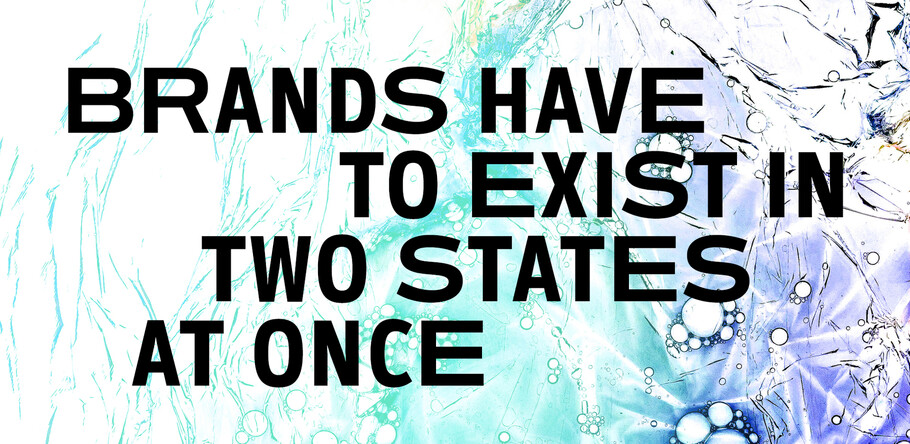
Wie Ihre Marke auch auf kurvenreichen Kundenreisen die Spur hält.
„ Manchmal braucht eine Marke nichts anderes als Schrift. Die muss dann aber auch richtig gut funktionieren. “
Moderne Marken sind schon lange keine statischen Gebilde mehr. Sie werden heute agil und anpassungsfähig geführt, ständig bereit, auf Veränderungen der Kundenerwartungen zu reagieren sowie neue Technologien und Herausforderungen aus anderen Märkten und Sprachen anzunehmen.
In gewisser Weise müssen Marken zwei Aggregatzustände gleichzeitig annehmen – fest und formbar, so dass sie ihr Kontur jederzeit dehnen können, ohne das innere Gerüst zu gefährden. In der Natur leistet Vergleichbares nur Wasser, das fließen, gefrieren und verdunsten kann, in den Bergen seinen Weg findet und riesige Ozeane füllt, dem Wesen nach aber immer es selbst bleibt.
Das Ziele eines jeden Markenmanagements ist die flexible Marke, die es Mitarbeitern und Teams erlaubt, mit ihr zu experimentieren und sie anzupassen, wobei ein solides Inneres dafür sorgt, dass sie nicht auseinander fällt.
Die unheimlich expandierende Marke.
Laut Adobe geben 71 Prozent der Unternehmen an, heute zehnmal so viele Bausteine zu erstellen wie zu Beginn des mobiles Zeitalters. Diese bemerkenswerte Zahl verdeutlicht den vielleicht wichtigsten Aspekt beim Branding von heute: Der Weg zum Kunden führt in mehr als nur eine Richtung.
„ 71 Prozent der Marken erstellen heute zehnmal so viele grafische Bausteine wie zu Beginn des mobilen Zeitalters. “
Stattdessen erweist sich die Customer Journey heute als ein zunehmend fragmentiertes Netz aus divergierenden Strömen. Die Reise eines jeden Kunden weist einzigartige und manchmal subtile Unterschiede auf, selbst wenn sie alle an ähnlichen Orten beginnt oder endet, zum Beispiel auf einem Mobilgerät. Es gibt Tausende unterschiedlicher Modelle, die weltweit in Benutzung sind, mit einem breiten Spektrum an technischen Möglichkeiten und einem noch breiteren Spektrum von Benutzerinnen und Benutzern. Kein einzige Kundenerfahrung ist mit einer anderen identisch.
„Die Kunden sind an mehr Orten als je zuvor, rein geografisch aber auch hinsichtlich der Hardware und des Betriebssystems, das sie benutzen“, sagt James Fooks-Bale, Creative Director bei Monotype. „Und wenn man glaubt, sich optimal eingerichtet zu haben, kommen schon wieder Nachfolgemodelle, eine neue Plattform oder eine neue Art der Content dazu“, ergänzt er.
Wir sind sicherlich noch nicht am Ende dieser Entwicklung angekommen. Schon in naher Zukunft können Marken mit neuen Innovation, Expansionen und mit einer Verlagerung der Kundenerwartungen rechnen, was die Menge und die Vielfalt der Berührungspunkte, die eine Marke zu managen hat, weiter diversifizieren wird. Auch wenn viele auf eine Verlangsamung dieser Dynamik hoffen: neue Technologien in den Bereichen Automatisierung, Personalisierung, Virtual Reality, mehr Plattformen und verbesserte Hardware deuten eher drauf hin, dass die industrielle Welt sich weiter verzweigt.
Schriften sind eine unverwüstliche Klammer.
Auch die flexibelste Marke braucht immer etwas, das sie zusammenhält, was die Kunden mit ihr verbindet, während diese durch Ebbe und Flut schifft. Dieses „Etwas“ ist die Hausschrift der Marke.
In einem perfekten Kommunikationsumfeld definiert sich eine Marke durch diverse visuelle Bausteine, darunter Logo, Farbe, Form, Bilder, Animationen, Sound und natürlich die eigene Schrift.
Doch wenn die Mobile-First-Ära eines bewiesen hat, dann ist es die Tatsache, dass Marken manchmal mit weniger Mitteln erkennbar bleiben müssen. Manche visuellen Komponenten müssen für mobile Geräte vereinfacht werden oder entfallen komplett, wobei der Fokus stets auf Klarheit und Benutzerfreundlichkeit liegt, ohne sich von der Markenidentität abzukoppeln. Im Gegensatz zu anderen Markenmerkmalen ist die Schrift – als visuelle Stimme – erstens eine unverzichtbare, tragende Komponente, und zweitens eine sehr robuste, weil das menschliche Auge selbst bei einem schlecht aufgelösten Text das Muster einer Markenschrift dechiffrieren kann.
“Wir haben in den letzten Jahren die enorme Beschleunigung der Marken-Wahrnehmung durch die Mobilgeräte erlebt“, sagt Fooks-Bale. „Wenn etwas mobil nicht funktioniert, funktioniert es per se nicht, Punkt. Es kann keine Kompromisse geben, wenn es um das Aussehen, das Gefühl oder die Inhalte des mobilen Erlebnisses geht. Schriften werden auch weiterhin eine maßgebliche Rolle in diesen Medien spielen, wo alles ineinander greift und die Kette nur so stark sein kann wie ihr schwächstes Glied“.
„ Wenn etwas mobil nicht funktioniert, funktioniert es per se nicht, Punkt. Es kann keine Kompromisse geben, wenn es um das Aussehen, das Gefühl oder die Inhalte des mobilen Erlebnisses geht. “
James Fooks-Bale, Monotype Creative Director.
Ein unverwechselbare, durchdacht entwickelte Schriftfamilie kann die Stimme einer Marke auch ohne die Unterstützung weiterer Branding-Elemente tragen … was wir spätestens seit Einführung von Schrift Corporate ASE bei Mercedes-Benz wissen. Das Kommunizieren mit einer exklusiven Hausschrift ist der einfachste Weg, um über alle Berührungspunkte hinweg Kontinuität zu gewährleisten. Selbst die miese Schwarzweiß- Kopie einer Rechnung wird sofort mit der dahinter stehenden Marke in Verbindung gebracht, wenn der Text in der Hausschrift gesetzt ist … so einfach geht visuelle Identität. Das funktioniert erst recht bei einer mobilen Website, nur Text, aber in Farbe und in hoher Auflösung.
Markenmanager können nicht immer allen über die Schulter schauen und würden am liebsten ganz darauf verzichten. Daher: eine flexible Herangehensweise an Ihre Marke, in deren Mittelpunkt eine durchdachte Font-Strategie steht, bringt allen im Unternehmen sofortigen Seelenfrieden.